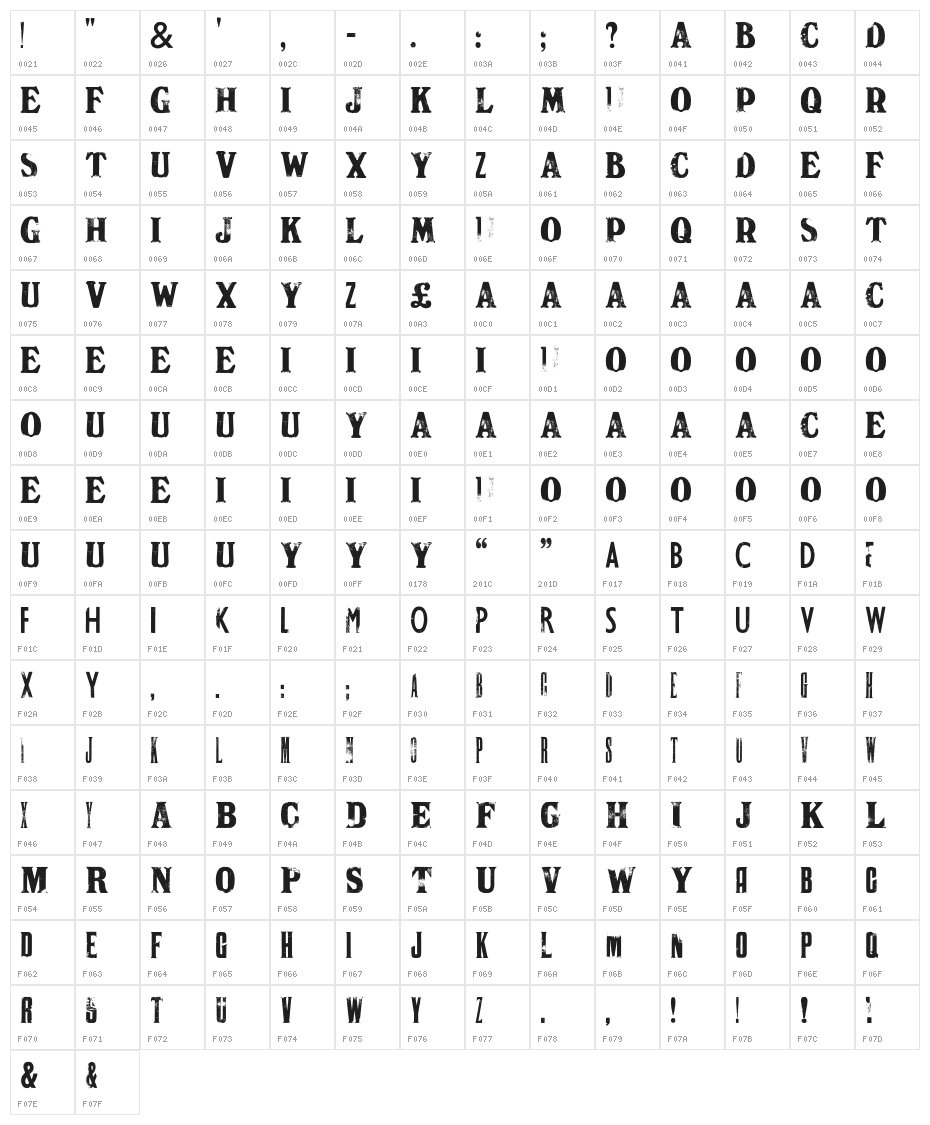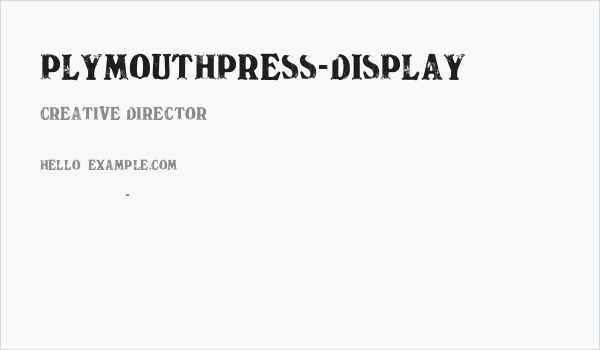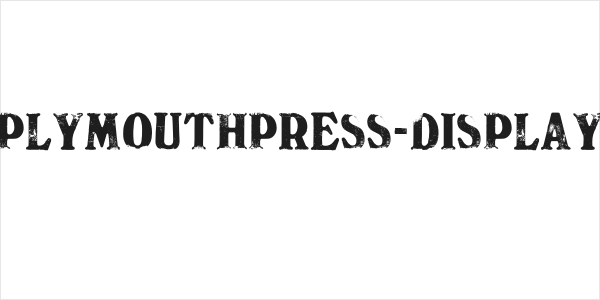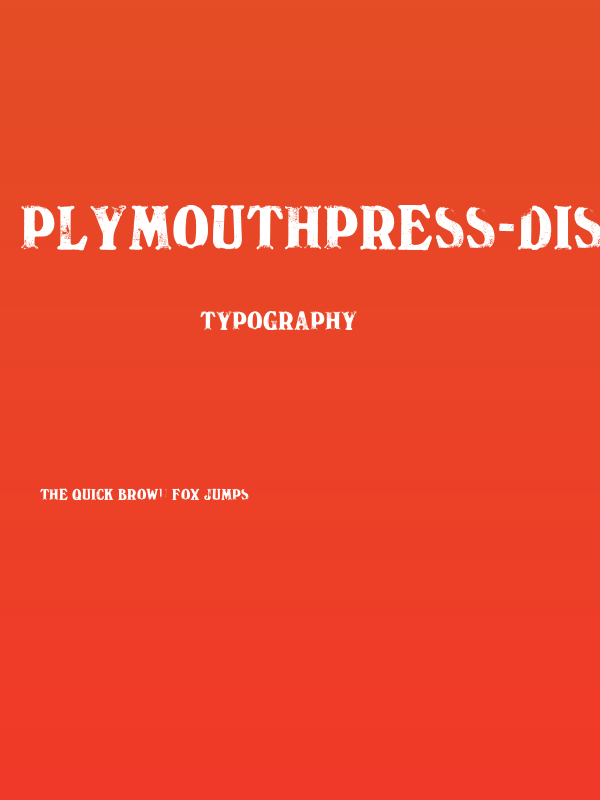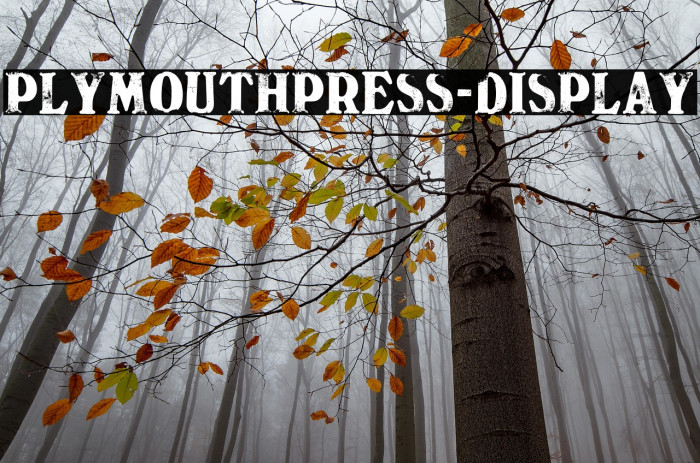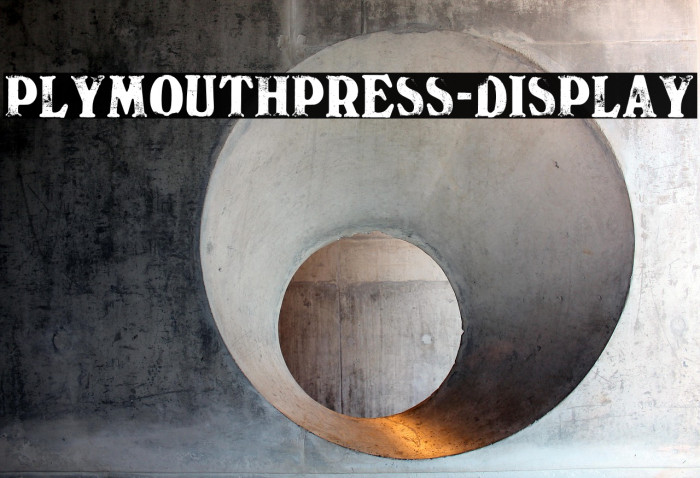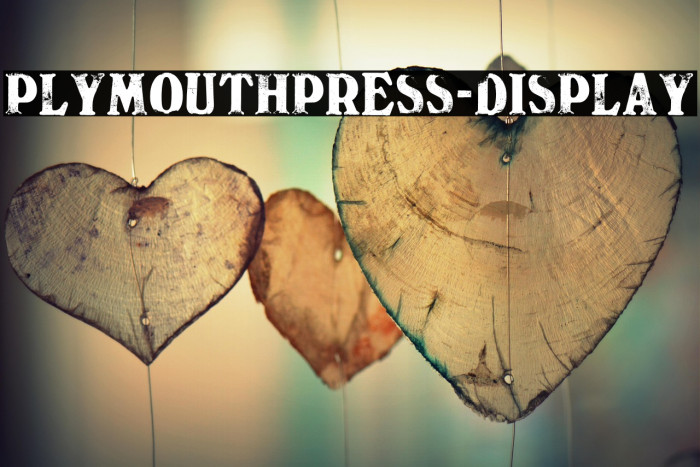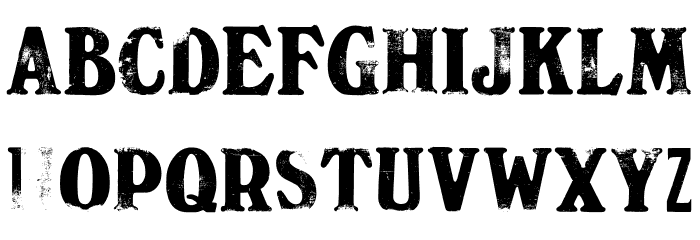
PlymouthPress-Display Font
| Kategorien | Retro |
| Gesamtstil | Vintage |
| Anwendungsfall | Logos, Headlines, Posters |
| Vorgeschlagene Projekte | Ideal for branding, posters, and packaging that require a vintage or handcrafted aesthetic. |